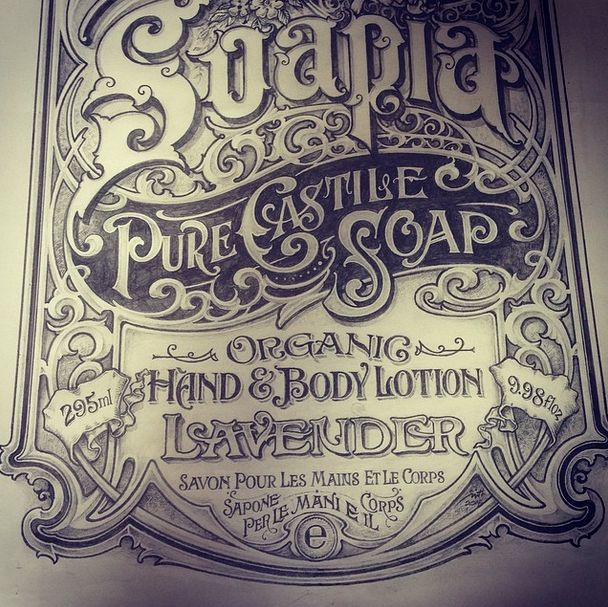
Шрифты под старину русский. Церковно-славянские шрифты
В своём знаменитом очерке «Украшение и преступление» 1908-го года модный тогда архитектор Адольф Лоос писал: «Развитие культуры влечёт за собой вытеснение орнаментальности из оформления повседневных вещей». Этим утверждением он исключал множество вычурных декоративных шрифтов, разработанных на протяжении прошлых столетий, из применения в дизайне высокого класса. А теперь быстренько вернёмся в наши дни: в Web 3.0 полно почти ровных шрифтов без засечек и классических прямых шрифтов, поэтому дизайнерам так не хватает излишеств книгопечатников былых времён.
Возьмите на вооружение мощную выразительность антикварных шрифтов и придайте вашей графике очарование старины, очень модное сейчас и в печатных, и в онлайн-проектах. От ковбойского и викторианского стилей до авангарда и каллиграфии — выбор весьма широк. Шрифты сгруппированы произвольно, современные интерпретации могут соседствовать с (почти) подлинными прототипами.
Имитации оттисков с деревянных досок и плакатные шрифты
Этот напоминающий дешёвые оттиски с деревянных досок шрифт не лишён своего шарма: от него веет блёклыми афишами захудалого театрика. Вид в равной степени мрачный и вызывающий, подходит для графики на сюжеты от неформальных до пугающих.
Circus Ornate Дитера Штеффманна (Dieter Steffmann) создаёт то же настроение, что и классическая графика на цирковые сюжеты, но сохраняет своеобразие в качестве орнаментального, броского плакатного шрифта.
Ещё один прекрасный псевдо-антикварный шрифт, созданный на основе плакатных литер19 века.
Typeology foundry позаимствовали и само начертание, и название у шрифта, разработанного в 1884 году Д. Т. Эймсом (D.T. Ames).
Ещё один псевдо-антикварный шедевр Дитера Штеффманна (Dieter Steffmann), Egyptienne Zierinitialen, превращает двухмерные буквы в роскошную объёмную резьбу.
Прелестный винтажный шедевр от Jester Font Studio.
Nasty — состаренный «ремикс», созданный Эдуардо Ресифи (Eduardo Recife) из шрифта Extra Ornamental, разработки House of Lime. Выпущен в двух вариантах, которые Ресифи также советует применять в сочетании друг с другом.
Разработчик ПО со свободной лицензией Дэвид Раковский (David Rakowski) создал этот шрифт в 1991 г. Спустя 17 лет, гармония монументальности и изящества в его очертаниях выглядит сенсацией из прошлого, которая сегодня производит неизгладимое впечатление.
Tuscan Рика Мюллера (Rick Mueller) — один из его многих винтажных шрифтов, который, однако, выделяется из общей массы затейливостью контуров в сочетании с весомой простотой.
Явное подобие Sideshow, разработки Harold’s Fonts, Fusty Saddle — вручную нарисованный, а затем оцифрованный шрифт ковбойского стиля. Bittbox предлагает вам не только гарнитуру своего шрифта, но и пояснение к нему: «fusty», как сказано на сайте автора, означает «старомодный и по сути, и с виду».
Цифровая версия оттиска с деревянной доски с явным стилистическим привкусом Дикого Запада, разработанная Мэтью Остином Пэтти (Matthew Austin Petty) из Disturbed Type. Словно заросшие ковбойской щетиной, грубо стёсанные края и неряшливые поверхности блочных элементов придают этому шрифту особый старинный налёт мужественности.
Продукт независимой студии цифровой полиграфии Fountain, Azteak сочетает в себе отголоски прошлого с мечтами о будущем. На механистическую основу этого шрифта наложены разные украшения, что навевает ассоциации с научно-фантастическими фильмами об альтернативном будущем в эпоху паровых машин.
Название этого шрифта — производное от фразы «ангел-хранитель» на французском языке, и его прописные буквы, действительно, венчаются фигурами крылатых стражей. Сочетание изящества и прочности контуров AngeGardien, общее у него с другими качественными винтажными шрифтами, возможно, и есть то самое, что стоит сохранить.
Антические и ренессансные шрифты
Подлинный шрифт 18 века кеслон (Caslon) мог бы сейчас выглядеть как Caslon Antique: слегка потёртым по краям, но не утратившим твёрдости. Данная интерпретация классического Caslon с засечками добавляет тексту взрослость и авторитетность без потери отчётливости.
Dominican — ещё один искусственно состаренный антикварный шрифт, причём, очень своеобразный, очертания которого навеяны особой прелестью старинных книг.
Необычный, состоящий из одних заглавных, шрифт Old Dog New Tricks вызывает интерес тем, что нижние элементы его, в принципе, классических букв с засечками опущены под линию строки.
Сочетание стиля ар-деко (Deco) с антикварными отголосками не позволяет с точностью проследить его происхождение, но, как учит теория «культуры повторной переработки» (remix culture), неожиданные варианты объединения компонентов приносят плоды в виде поистине уникальных явлений.
Разработанный Дэвидом Дж. Пэрри (David J. Perry) в 2003 году, Cardo предназначался для учебных пособий по классическим языкам и средневековой письменности. Остроконечные буквы этого шрифта напоминают как почерк летописцев, так и надписи, выбитые на камнях.